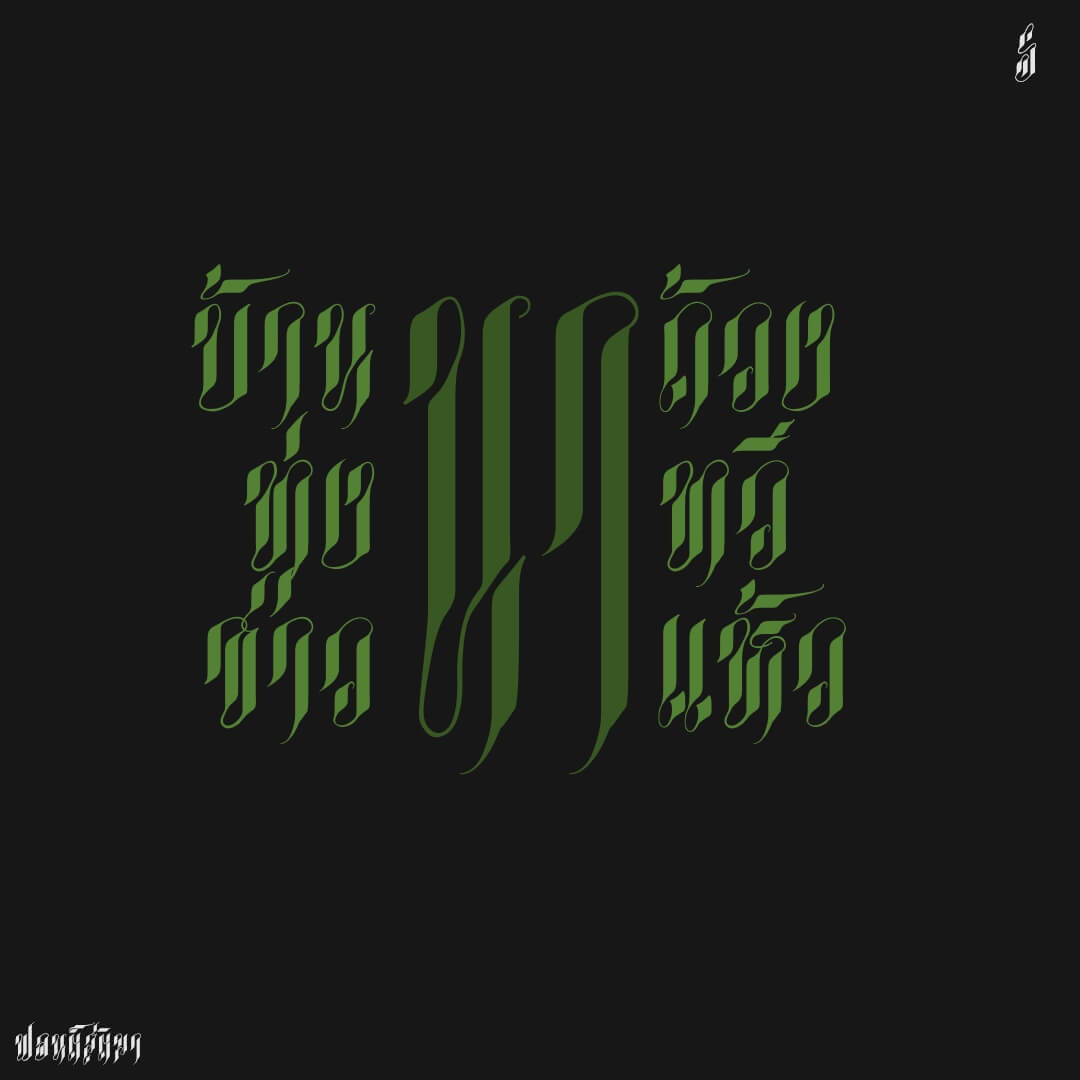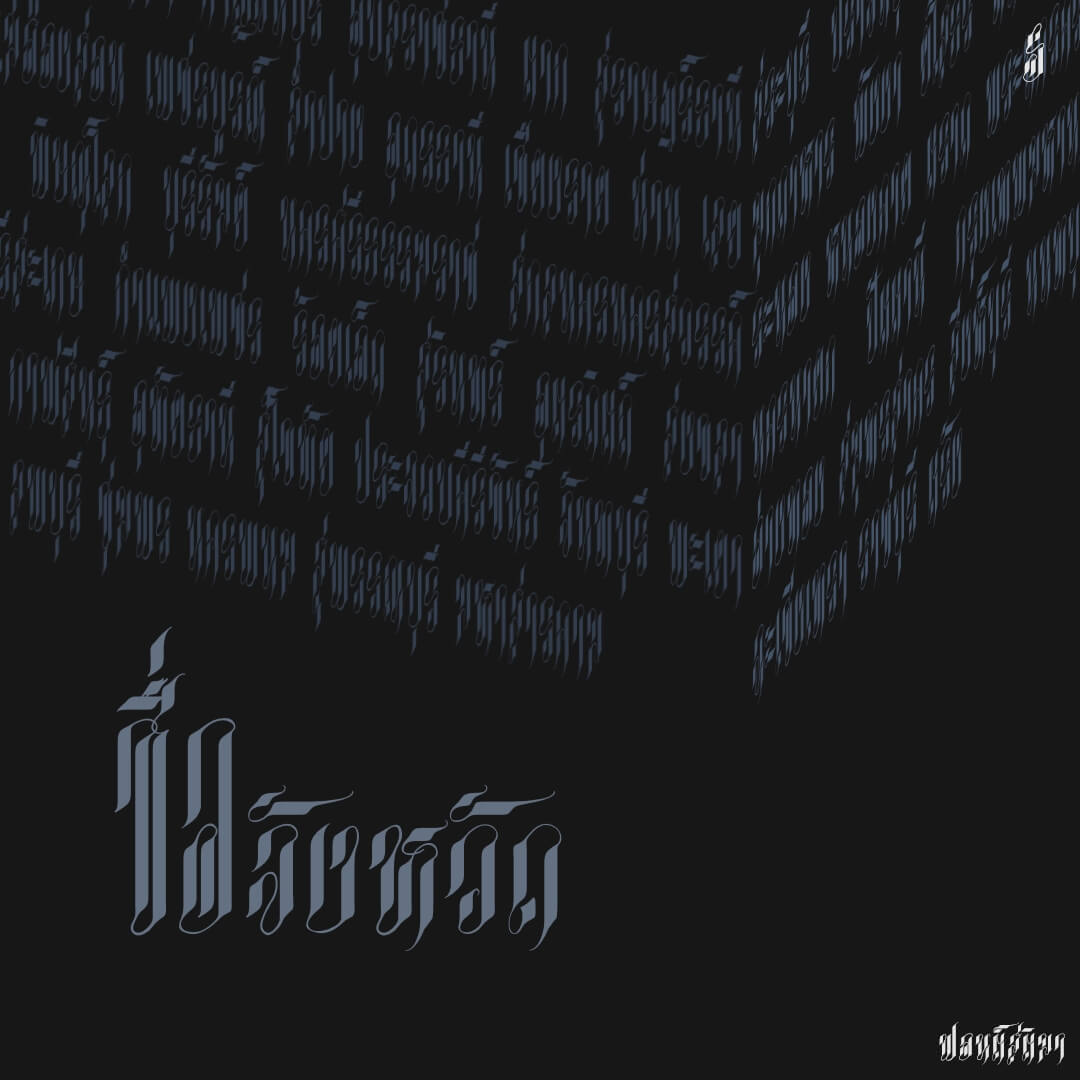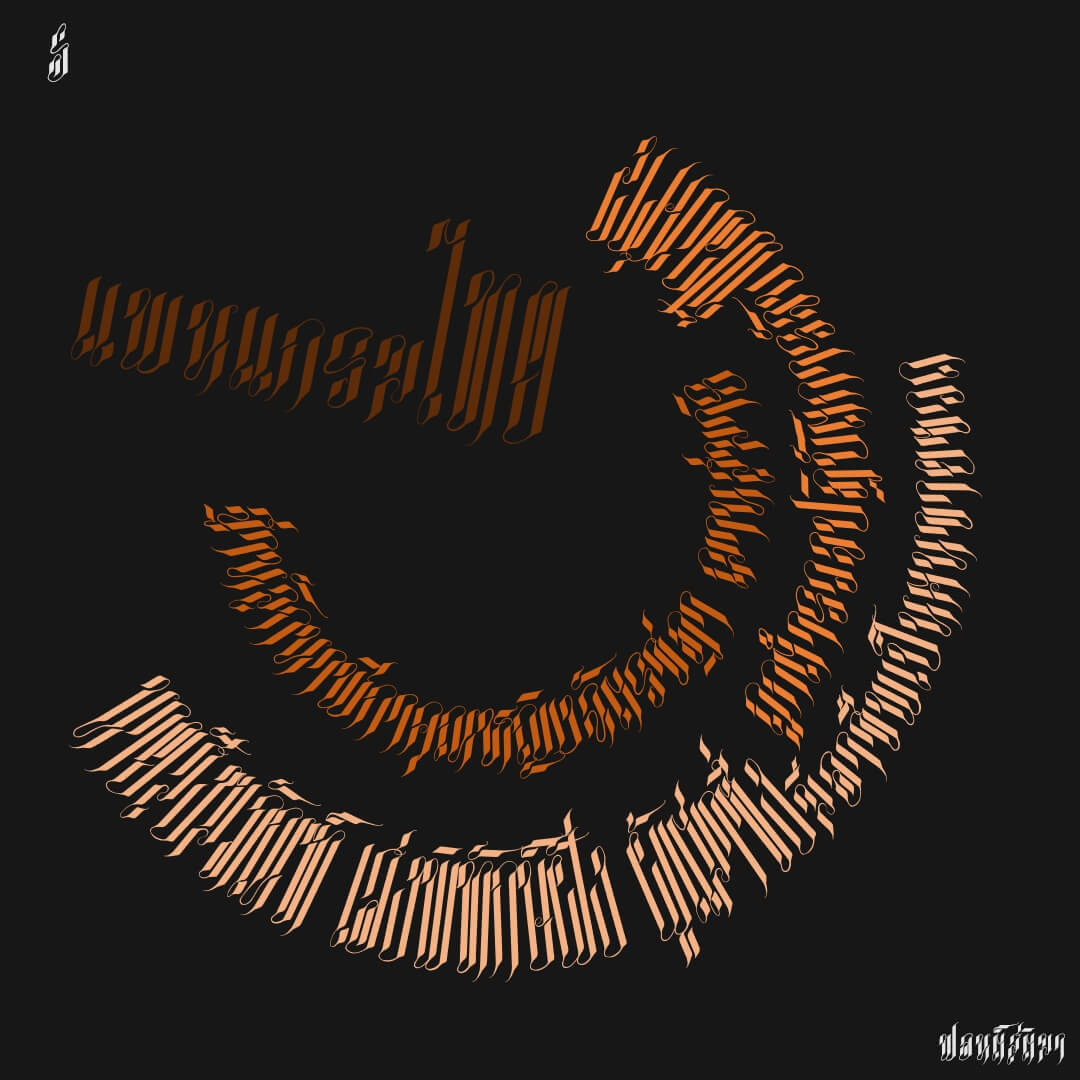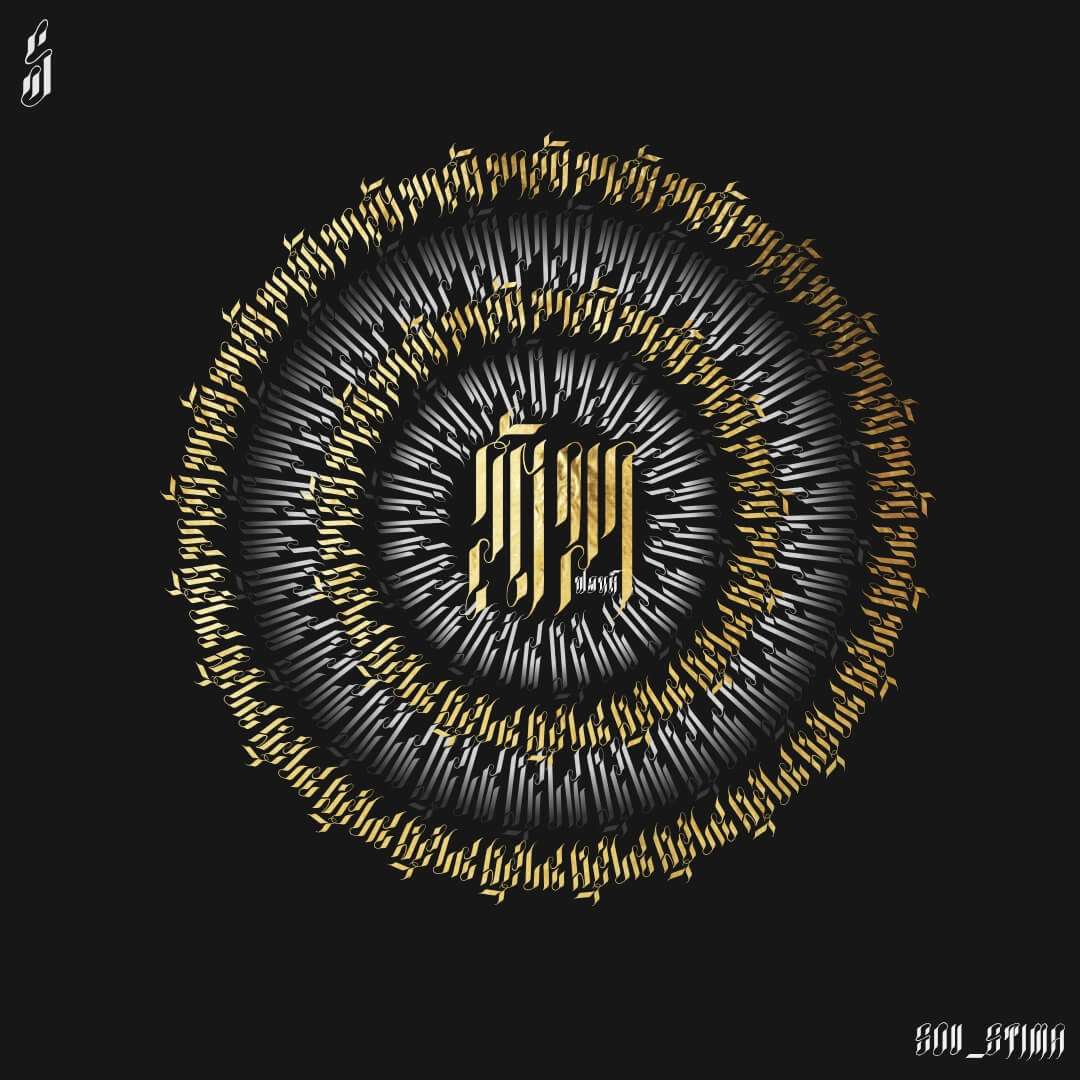
สติมา (SOV_StiMa)
Calligraphy logo อักษรวิจิตร อ่อนช้อย
ฟอนต์สติมา – ทำฟอนต์แนว calligraffiti แทนตัวเดิม โดยตั้งโจทย์ว่าอักษรหลักจะไม่ใช้เส้นขวาง ภาพรวมมันก็เลยไม่ค่อยมีความหลากหลายเท่าไร เลยเพิ่มตัวสูงปรี๊ดเข้าไปเสริมทัพ
เบื้องหลังการออกแบบ : ฟอนต์ สติมา